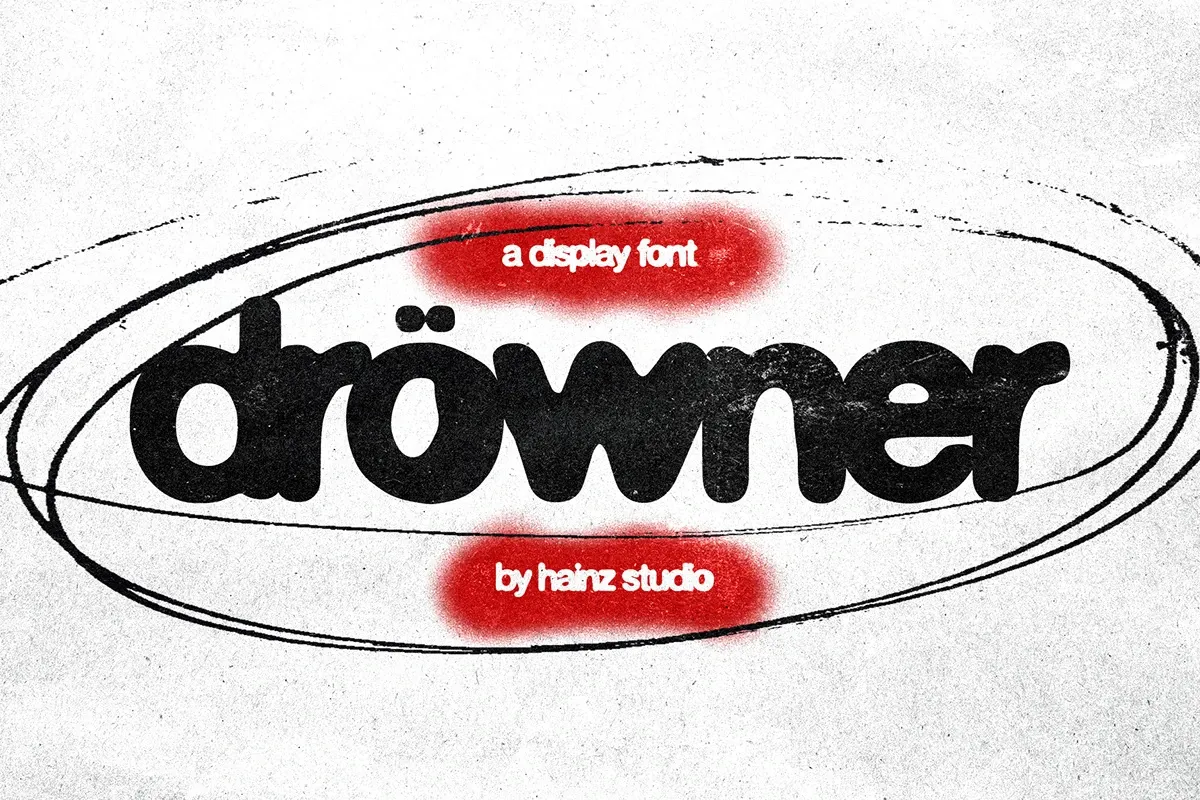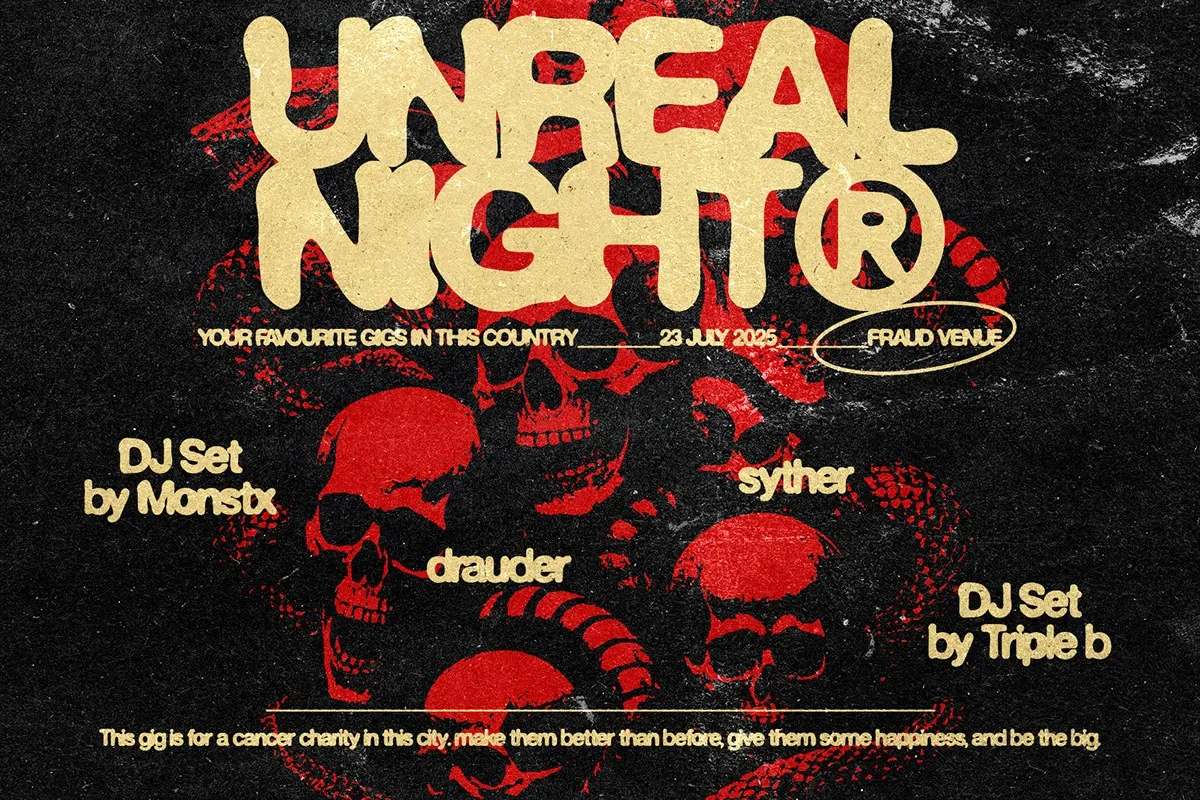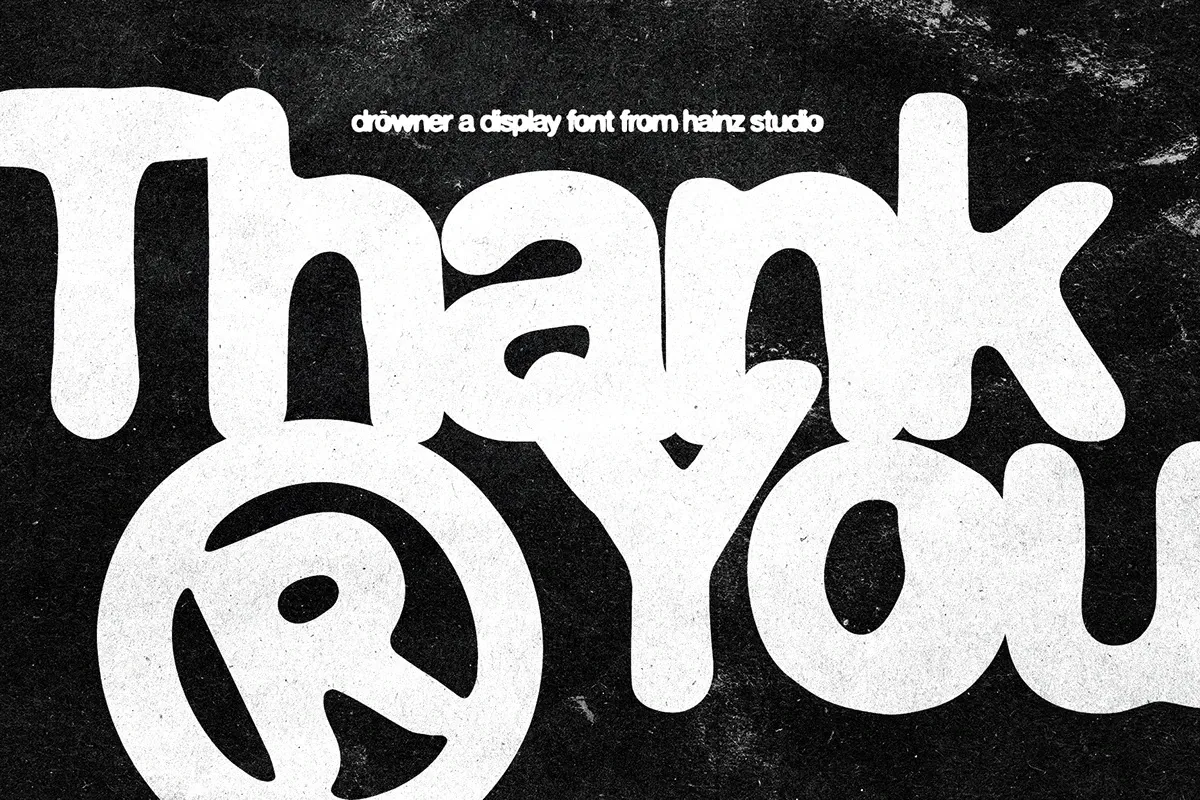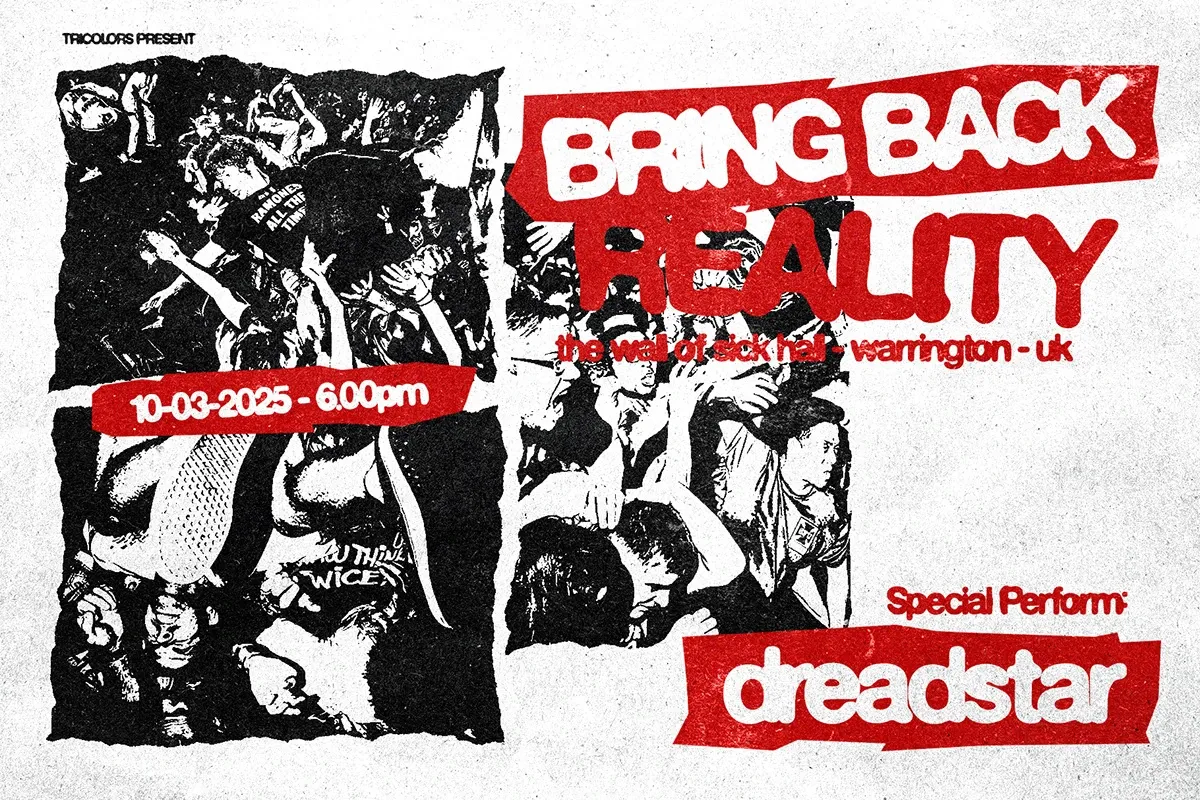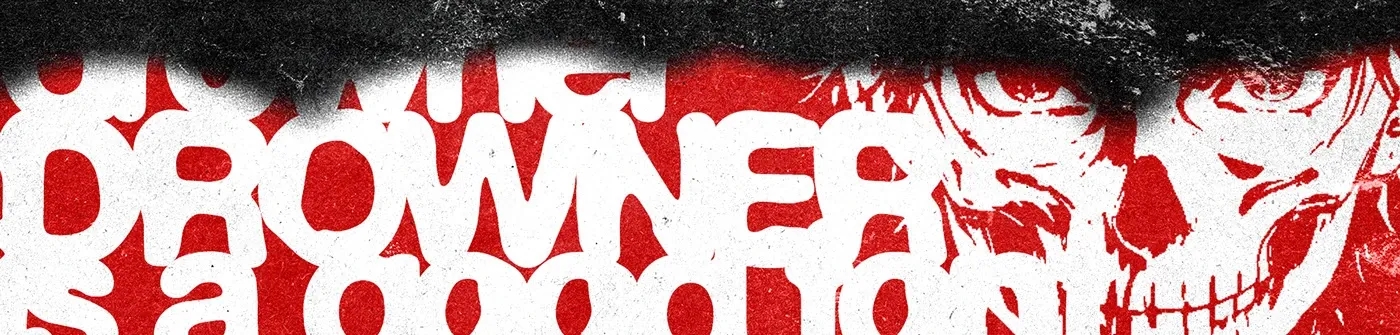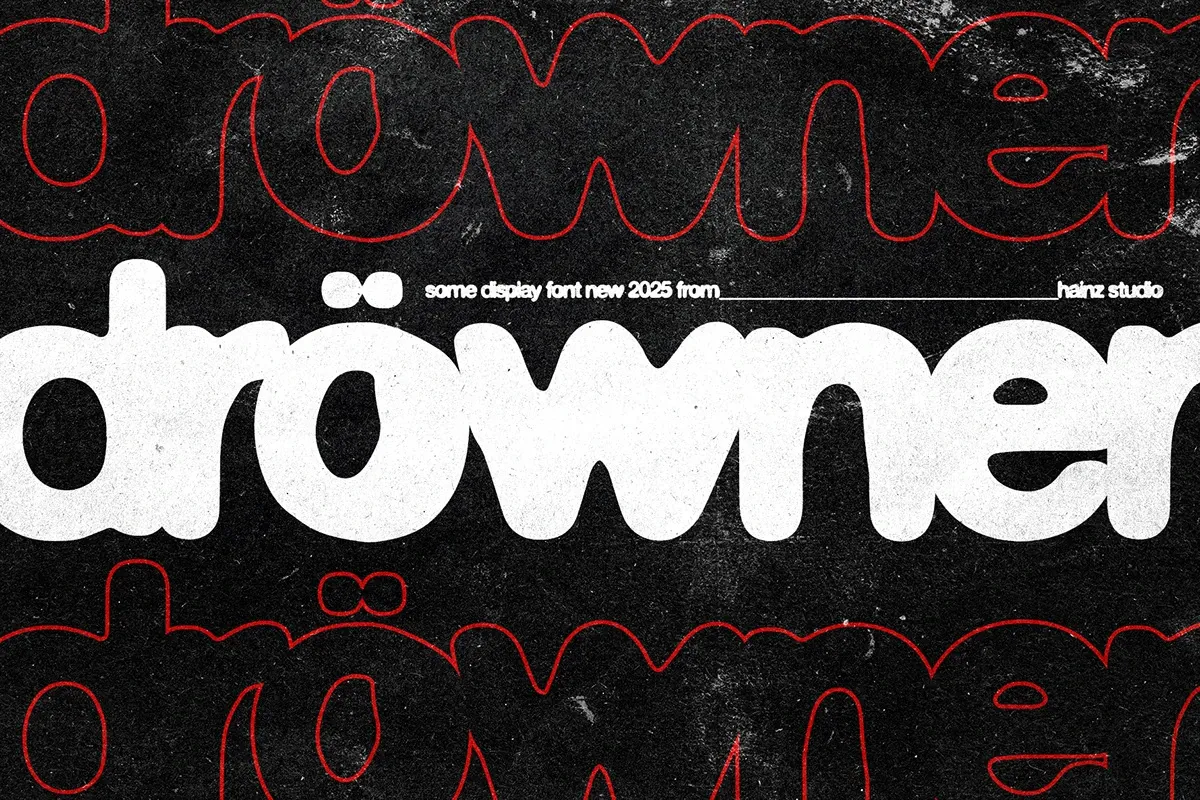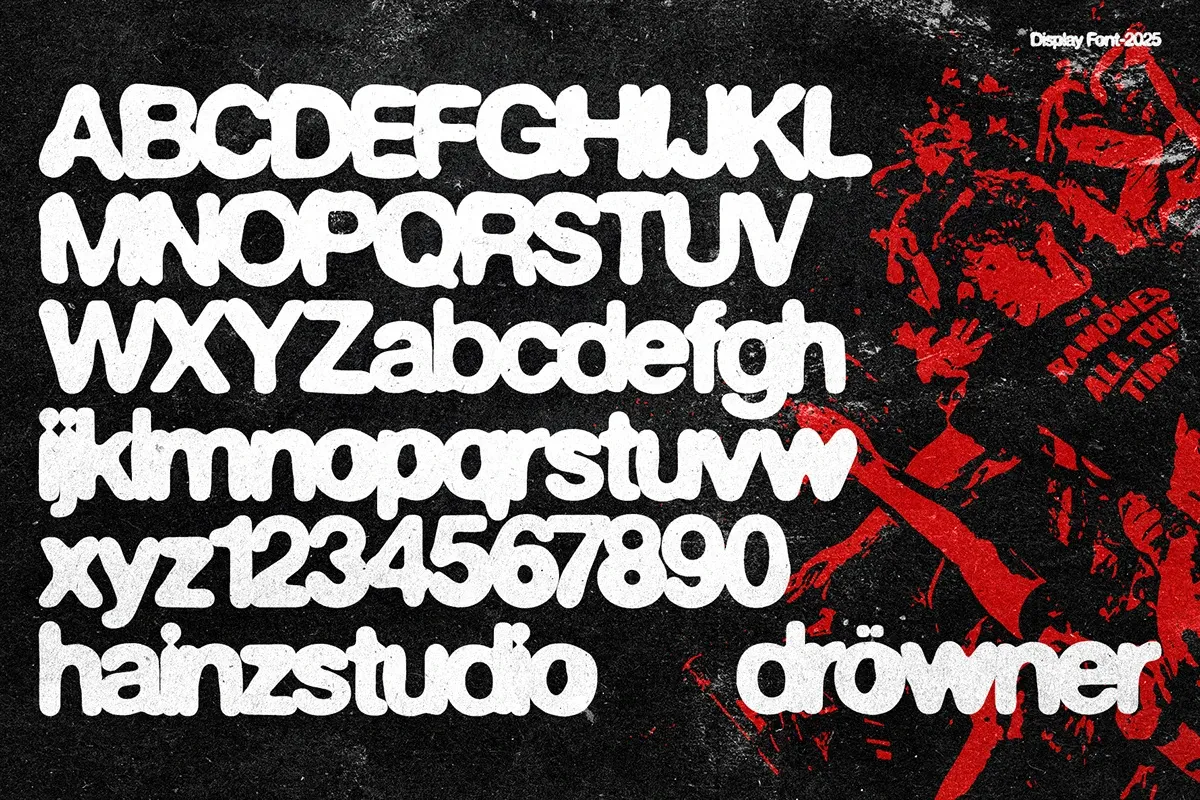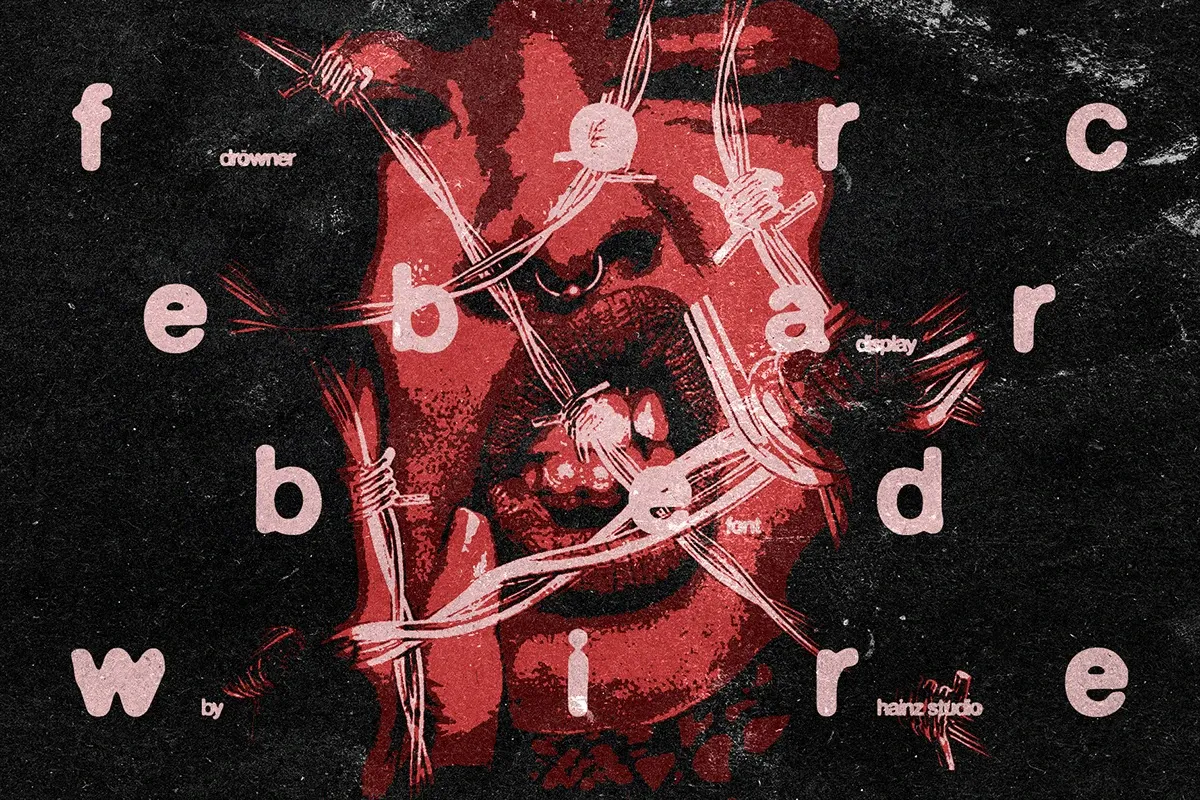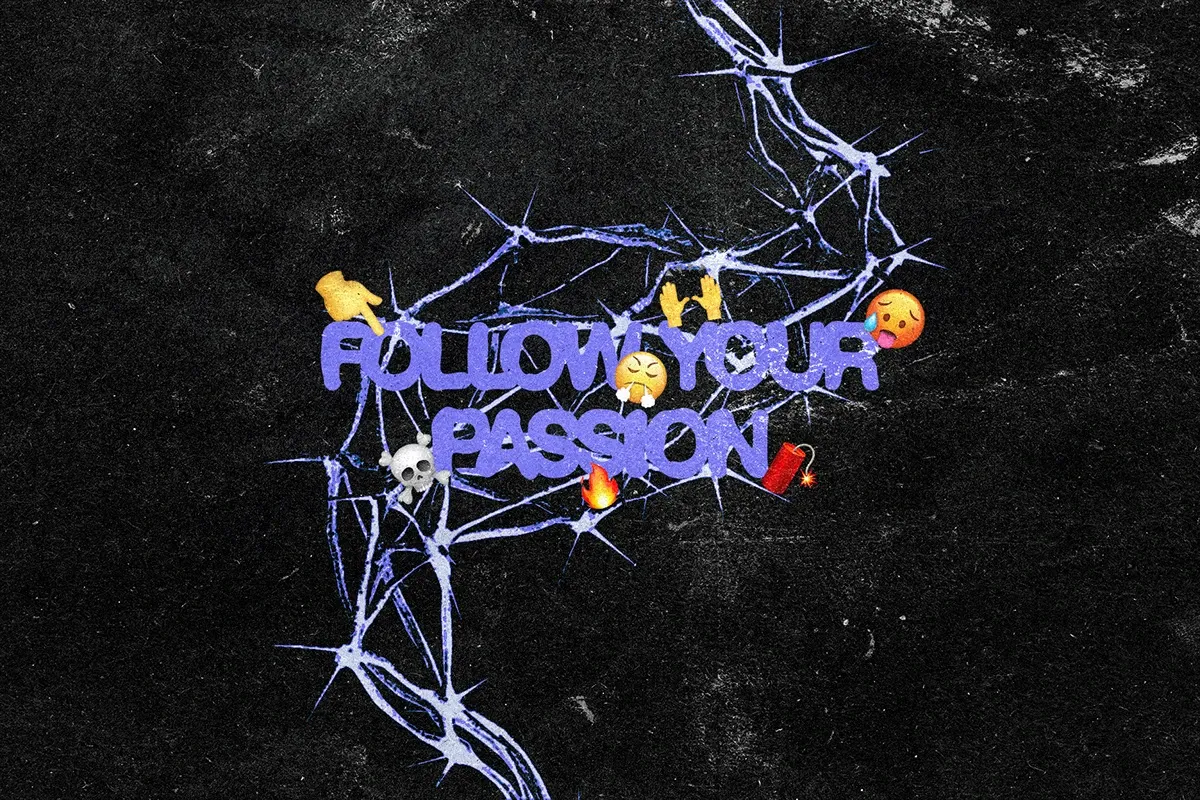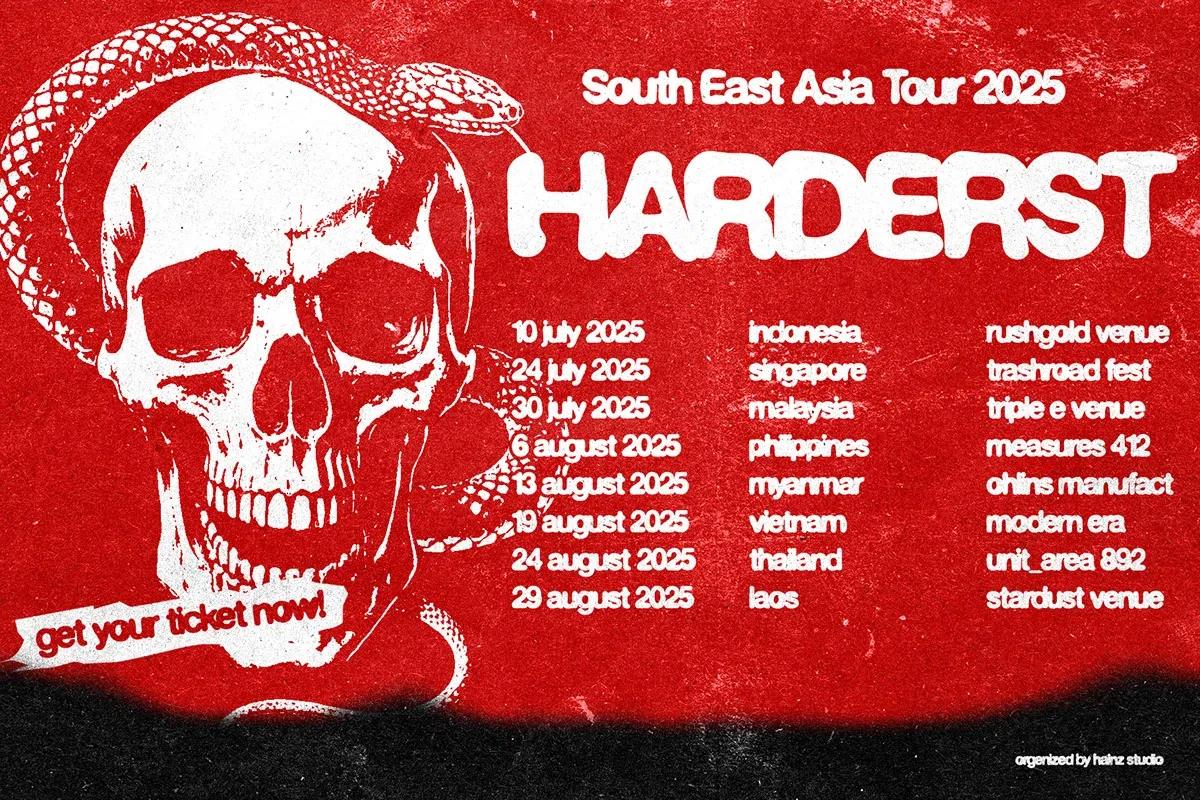
Drowner Display Font: Conheça e Baixe Grátis Essa Tipografia Única
Portanto, se você deseja renovar suas criações visuais, precisa conhecer a Drowner Display Font. Além disso, essa tipografia foi desenvolvida com um estilo moderno e marcante. Com efeito, ela une estética contemporânea e excelente presença visual.
O que é a Drowner Display Font?
Em primeiro lugar, a Drowner Display Font é uma família tipográfica incrível. Com efeito, o projeto foi elaborado focado em títulos e composições de alto impacto. Por essa razão, os criadores focaram com precisão nos detalhes geométricos e na personalidade do traço.
Assim, a fonte oferece uma atmosfera extremamente versátil. Consequentemente, ela atende desde projetos corporativos refinados até criações visuais mais ousadas e artísticas.
Destaques do Estilo Tipográfico:
Primeiramente, a fonte possui traços bem definidos. Por isso, garante forte presença visual. Além disso, funciona muito bem em títulos, logotipos e peças promocionais. Da mesma forma, é compatível com Photoshop, Illustrator, Figma e Canva.
Onde Utilizar a Drowner Display Font?
Em segundo lugar, a escolha tipográfica define a mensagem do seu projeto. Nesse sentido, a Drowner Display Font se adapta perfeitamente a várias aplicações visuais. Além do mais, ela garante excelente hierarquia visual.
1. Identidade Visual e Logotipos
Por exemplo, a fonte possui formas distintas e memoráveis. Por esse motivo, é ideal para marcas que buscam transmitir inovação e autenticidade. Consequentemente, a marca se destaca no mercado.
2. Redes Sociais e Banners
Contudo, o tempo de atenção nas mídias digitais é curto. No entanto, a Drowner Display Font ajuda a destacar títulos e chamadas para ação. Assim, sua postagem ganha mais engajamento.
3. Embalagens e Impressos
Por exemplo, embalagens e cartazes ganham bastante apelo visual. Desta forma, o produto final fica muito mais atraente no mostruário. Além disso, o acabamento fica impecável.
Dicas para Combinar a Drowner Display Font em Seus Layouts
Além disso, criar uma boa combinação tipográfica é essencial para qualquer designer. Por exemplo, você pode usar a Drowner Display Font em títulos chamativos. Em seguida, utilize uma fonte Sans-Serif neutra para o texto de apoio. Assim, o layout mantém o equilíbrio perfeito.
Da mesma forma, trabalhe bem o contraste de tamanhos entre as fontes. Por essa razão, evite usar a Drowner Display Font em blocos de texto muito longos. Desta forma, a leitura do usuário fica muito mais fluida e agradável.
Aplicações da Drowner Display Font em Projetos de Web Design
Ainda assim, a Drowner Display Font pode ser usada com sucesso no web design. Por exemplo, ela se destaca muito em banners principais de e-commerce. Além disso, landing pages ganham um visual muito moderno.
Conclusão